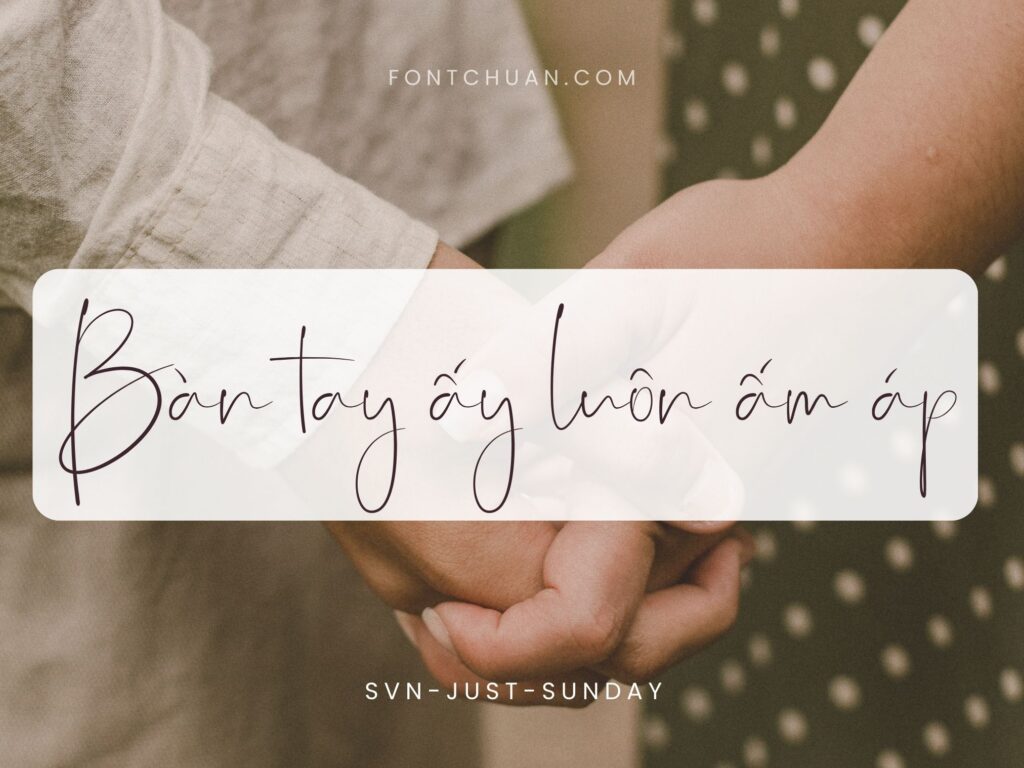
Font SVN Just Sunday Việt Hóa
Font SVN Just Sunday là phiên bản Việt hóa của kiểu chữ Just Sunday, được thực hiện bởi STYLEno.1 Fonts. Just Sunday là một kiểu chữ script hiện đại với phong cách nữ tính, mỗi ký tự được thiết kế tỉ mỉ để tạo nên vẻ đẹp mềm mại và thanh lịch. Font này phù hợp cho nhiều dự án thiết kế như logo, nhiếp ảnh, watermark, trích dẫn, tiêu đề blog, poster, thiệp cưới và thương hiệu thời trang. Phiên bản Việt hóa được cung cấp miễn phí cho mục đích sử dụng cá nhân.
SVN Just Sunday lý tưởng cho các dự án thiết kế yêu cầu sự mềm mại và thanh lịch, như thiết kế thiệp mời, logo thương hiệu và các ấn phẩm truyền thông. Các ngành nghề như thiệp cưới, giáo dục và ẩm thực có thể tận dụng font này để tạo điểm nhấn trong thiết kế. Ngoài ra, font cũng thích hợp cho các sự kiện như Valentine, Sinh nhật, Tết và các lễ hội khác.